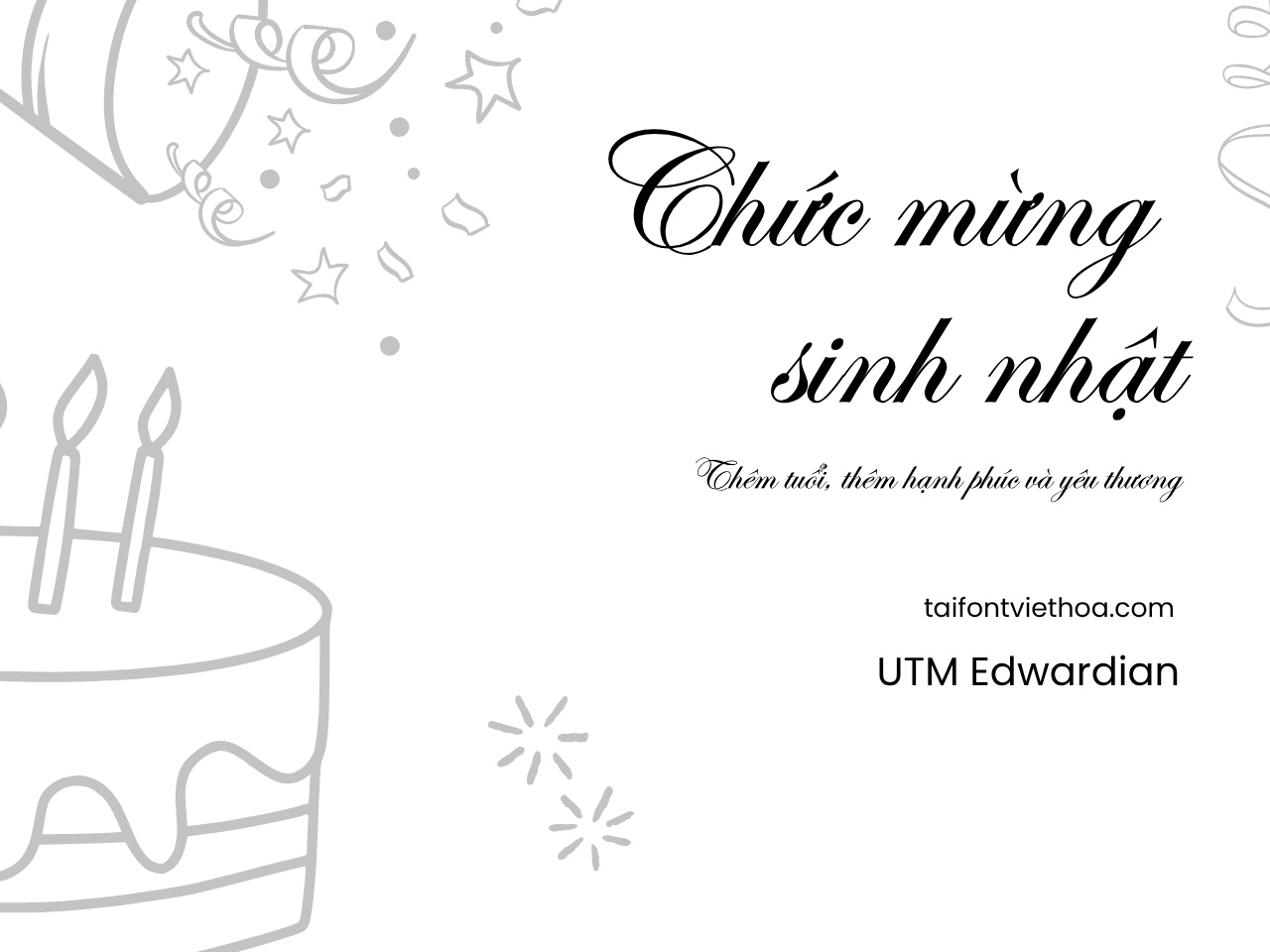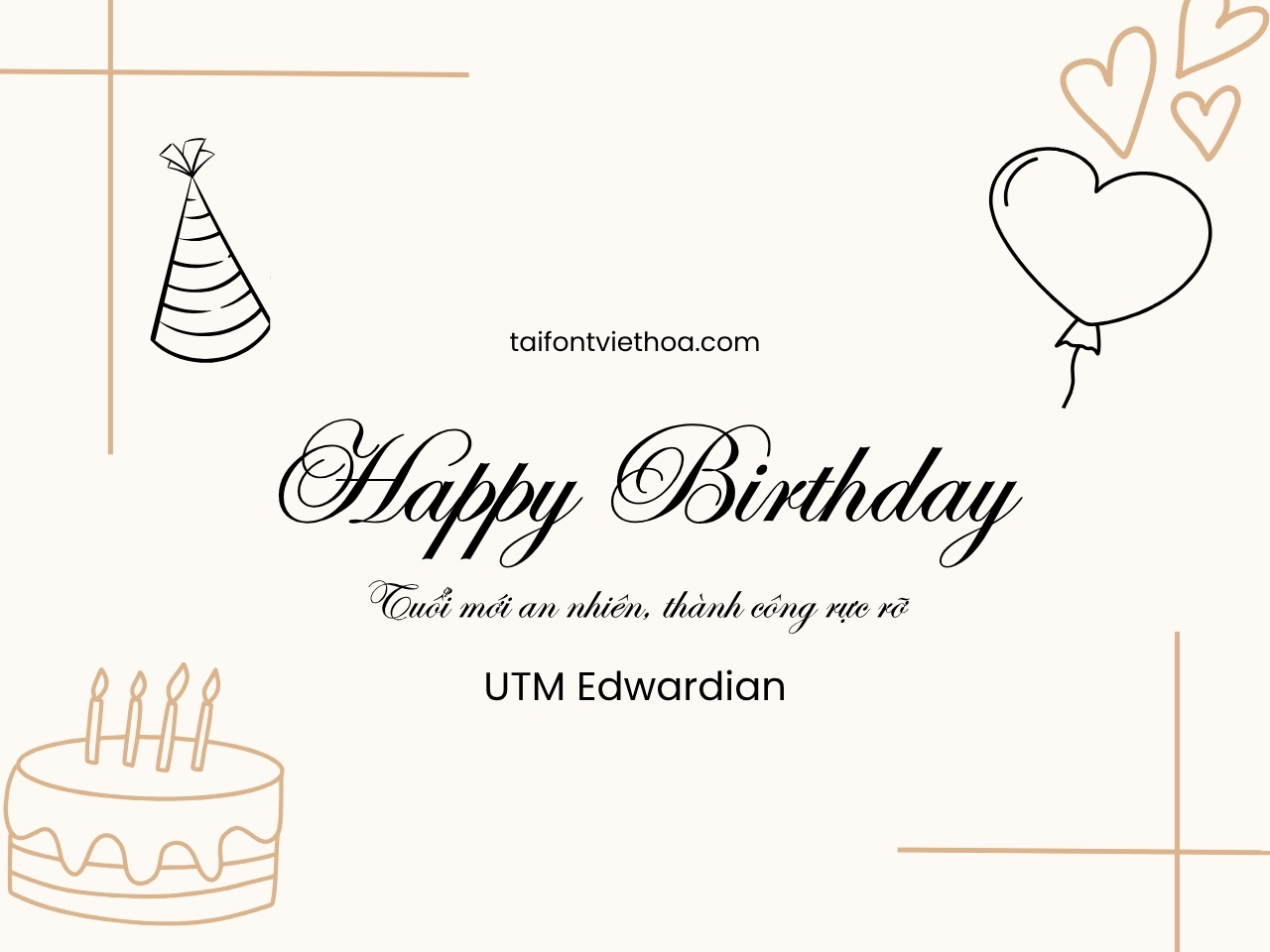
Font việt hóa UTM Edwardian
Giới thiệu về font UTM Edwardian
UTM Edwardian là phiên bản Việt hóa của font Edwardian – một kiểu chữ script thanh lịch, duyên dáng và trang nhã, lấy cảm hứng từ phong cách viết tay cổ điển. Font gốc nổi bật với các nét bút mảnh mai, uyển chuyển và các đường cong mềm mại, tạo nên vẻ đẹp lãng mạn và sang trọng. Phiên bản Việt hóa đã được hoàn thiện để hỗ trợ đầy đủ tiếng Việt cùng hơn 100 ngôn ngữ khác, mở rộng khả năng ứng dụng trong các dự án thiết kế cá nhân hóa và nghệ thuật.
Font UTM Edwardian được taifontviethoa.com sưu tầm và lựa chọn kỹ càng nhằm phục vụ cộng đồng thiết kế Việt Nam. Phiên bản Việt hóa giữ nguyên nét mềm mại và tinh tế của bản gốc, đồng thời tối ưu khả năng hiển thị tiếng Việt, rất phù hợp cho các dự án thiệp cưới, branding và truyền thông nghệ thuật.
Giới thiệu về font UTM Edwardian
Đặc điểm thiết kế và ứng dụng của UTM Edwardian
UTM Edwardian sở hữu cấu trúc script với các nét bút thanh mảnh, liên kết tự nhiên và các ligature đa dạng giúp tăng tính linh hoạt và biểu cảm trong thiết kế. Font có độ tương phản nhẹ nhàng, tạo cảm giác mềm mại, duyên dáng và lãng mạn, rất thích hợp cho các thiết kế mang phong cách cá nhân hóa và nghệ thuật cao.
Font thích hợp sử dụng trong các ứng dụng như thiệp cưới, thiệp mời, thiết kế logo thương hiệu mỹ phẩm, poster nghệ thuật, bao bì sản phẩm thủ công và các dự án truyền thông mang tính cá nhân hóa cao. Ngành nghề phù hợp gồm: tổ chức sự kiện, thời trang, làm đẹp, nghệ thuật sáng tạo, quảng cáo cá nhân hóa và thiết kế nội thất.